Этнические шрифты: культурные особенности в дизайнерских продуктах
Как дизайнеры используют допетровское письмо, древнюю письменность Нигерии и очертания мексиканских суккулентов.
Чтобы подчеркнуть архетипические образы, традиционность, историческую и социальную ценность разных народов, дизайнеры используют этнические шрифты. Хотя в них отсутствует геометрическая строгость, они помогают сильнее показать индивидуальность проекта и передать ощущение национальной идентичности.
Рассказываем, как славянские, африканские, индейские и другие этнические шрифты отражают культурные особенности в дизайнерских продуктах.
- почему в названии африканских шрифтов не стоит использовать слово tribal;
- для каких целей лучше всего подходят шрифты с особенностями коренных народов Америки;
- о чём нужно помнить при создании мультикультурных шрифтов;
- какие культуры помогут вдохновиться на создание своего этнического шрифта.
Славянские
Основа первых старославянских шрифтов — глаголица, в которую Кирилл и Мефодий добавили петлеобразность. Славянские этнические шрифты традиционно используют в исторических и национальных проектах, хотя они могут служить для усиления «русскости» в современной фешен-индустрии, упаковке и брендинге.
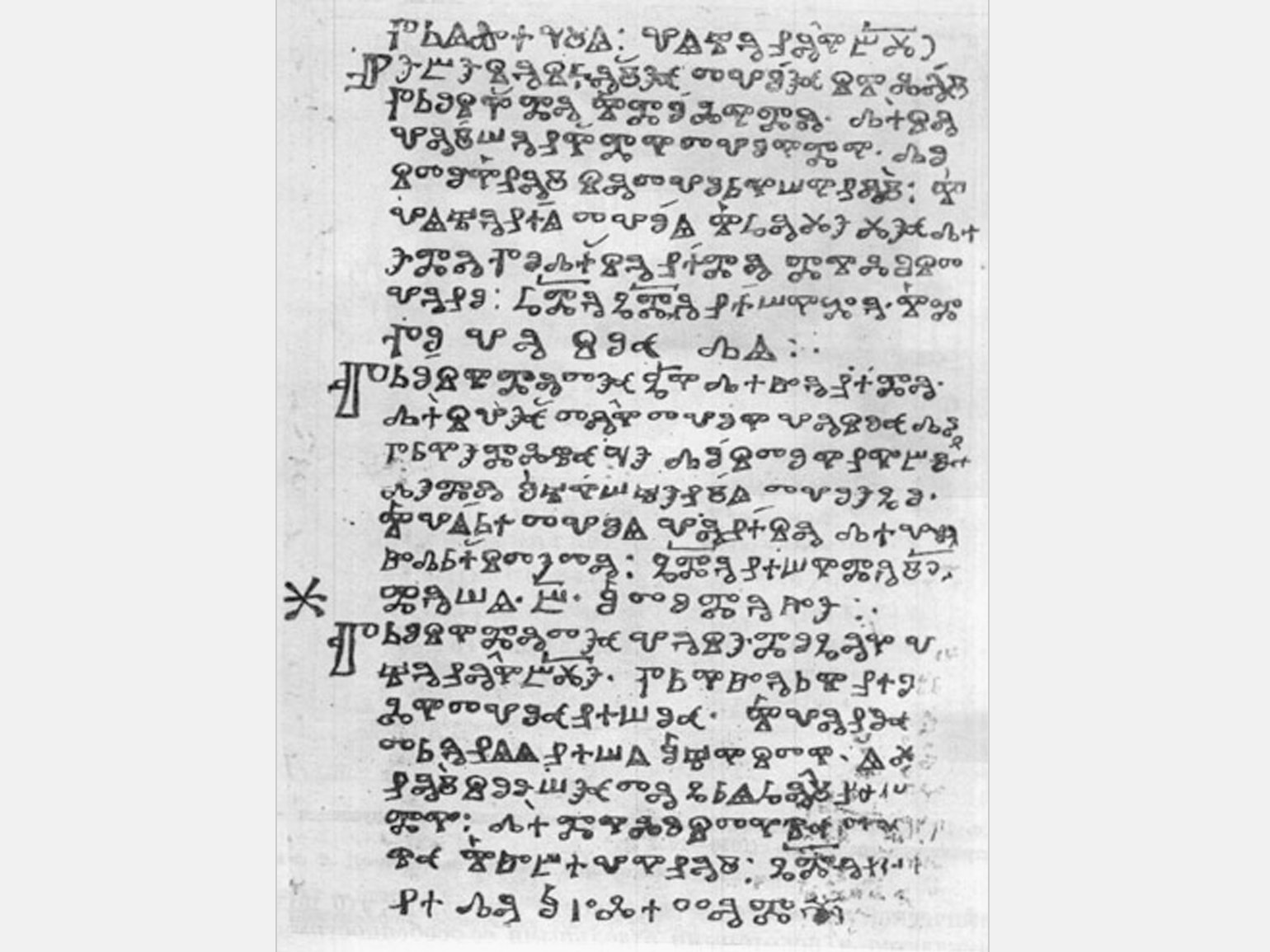
Юрий Остроменцкий
Графический и шрифтовой дизайнер, выпускник кафедры «Художественно-техническое оформление печатной продукции» МГУП, сооснователь магазина type.today и студии CSTM Fonts. Проекты CSTM Fonts получали награды в конкурсах European Design Awards, Granshan и «Современная кириллица».
Славянские шрифты нельзя назвать универсальными, потому что в зависимости от контраста, рисунка знаков и других деталей шрифт стилистически будет соответствовать определённой географии, веку или даже конкретной книге. Шрифты Times New Roman или Helvetica по рисунку никогда не были нейтральными или универсальными, но стали таковыми в силу частоты использования. Они так примелькались, что отчасти утратили выразительность.
Например, шрифт Izhitsa так часто используют в старославянском контексте, что его уже можно назвать универсальным, хотя у него есть конкретный исторический прототип.
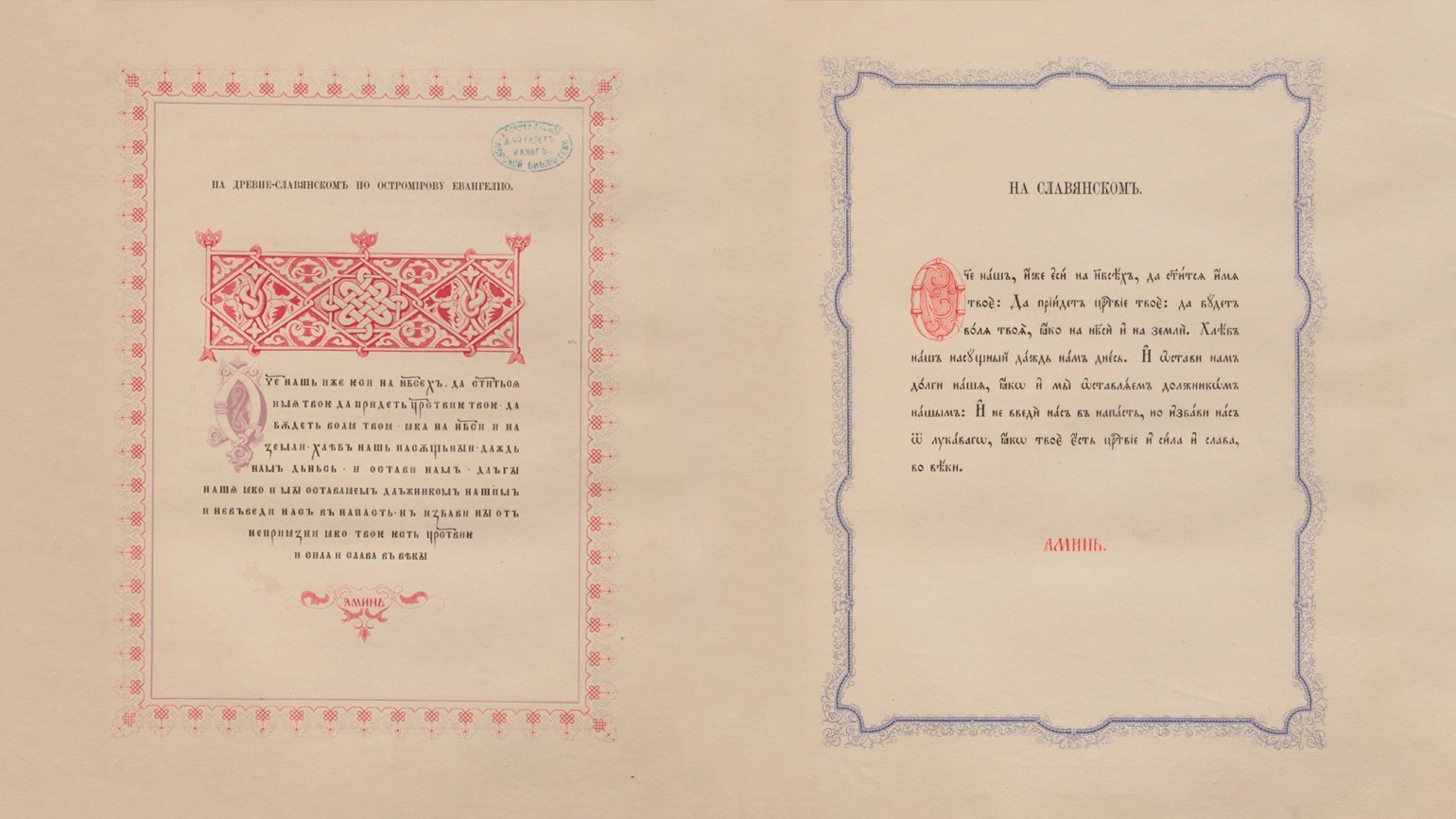
Дефицит качественных славянских шрифтов в науке и дизайне действительно существенный. Мне довелось общаться на эту тему с Виктором Марковичем Живовым, а сейчас я принимаю участие в переиздании работ Зализняка. Шрифтов, которые учёные могли бы использовать одновременно и в книге про Остромирово Евангелие, и про берестяные грамоты, — и вовсе не существует. Существующие шрифты чаще всего стилистически обращены к определённому времени и месту, что для учёных неприемлемо.
Сейчас я работаю над допетровским шрифтом с минимальными отсылками к веку или работе конкретного автора. Избавляюсь от контраста и ярко выраженных деталей, оставляя скелет знака. В этом суть моего эксперимента — что-то упростить, а что-то сохранить, чтобы шрифт стал современным, достаточно нейтральным, но при этом безусловно допетровским.
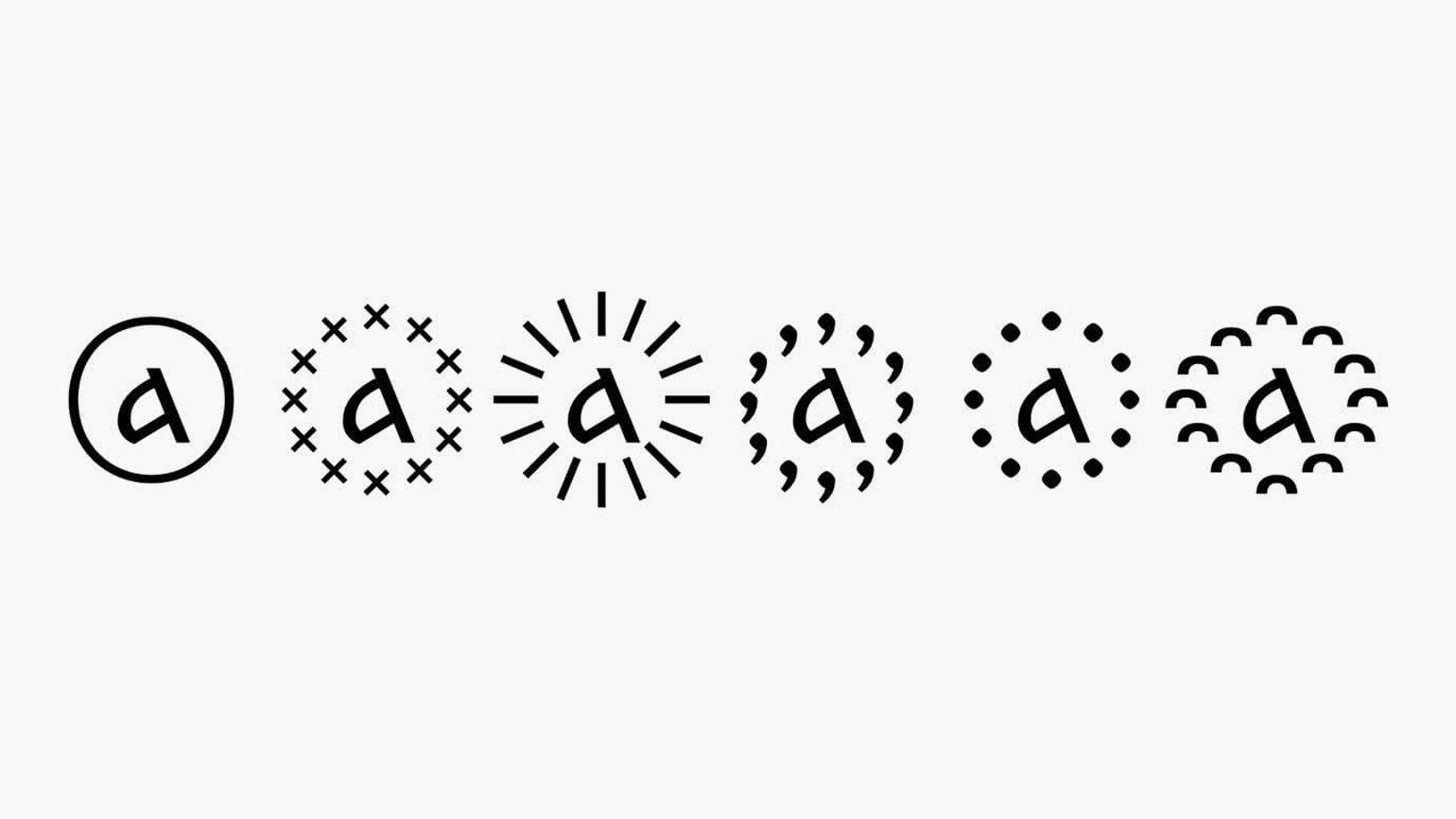
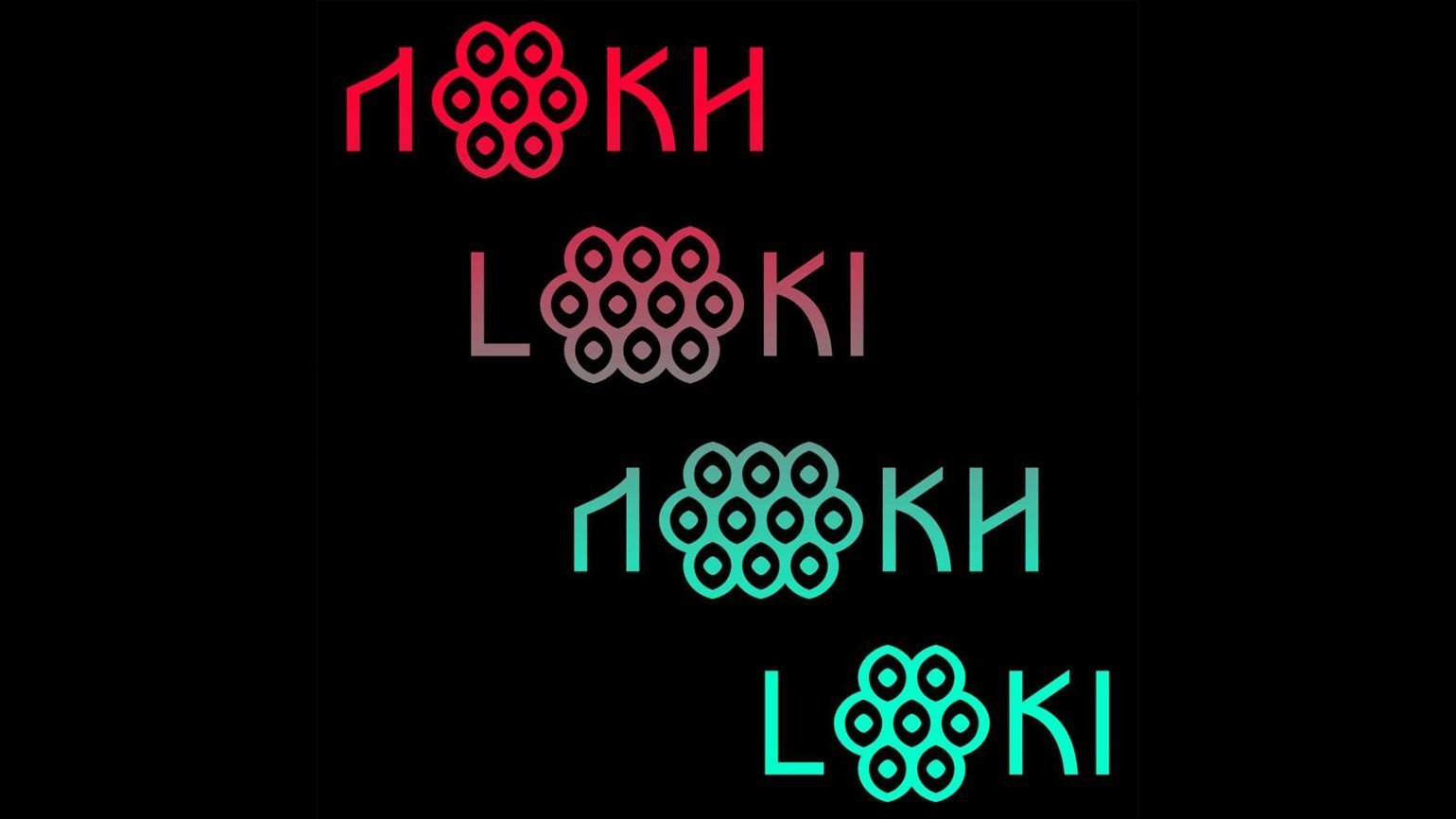
Мне кажется, что сейчас допетровский шрифт может выглядеть очень актуально. Например, мне нравится, как остромодно выглядит старославянская графика в коллекции Гоши Рубчинского.
Допетровская эстетика захвачена религиозно-национальной тематикой. Хочется, чтобы мы могли оценить красоту и выразительность этих букв вне идеологий и коннотаций. Мы могли бы относиться к допетровскому шрифту так же, как европейская культура относится к готическому, и использовать его вне идеологий. Я считаю, что у любого из нас ровно столько же прав на старославянский шрифт, сколько и у институций, связанных с религией и историей.
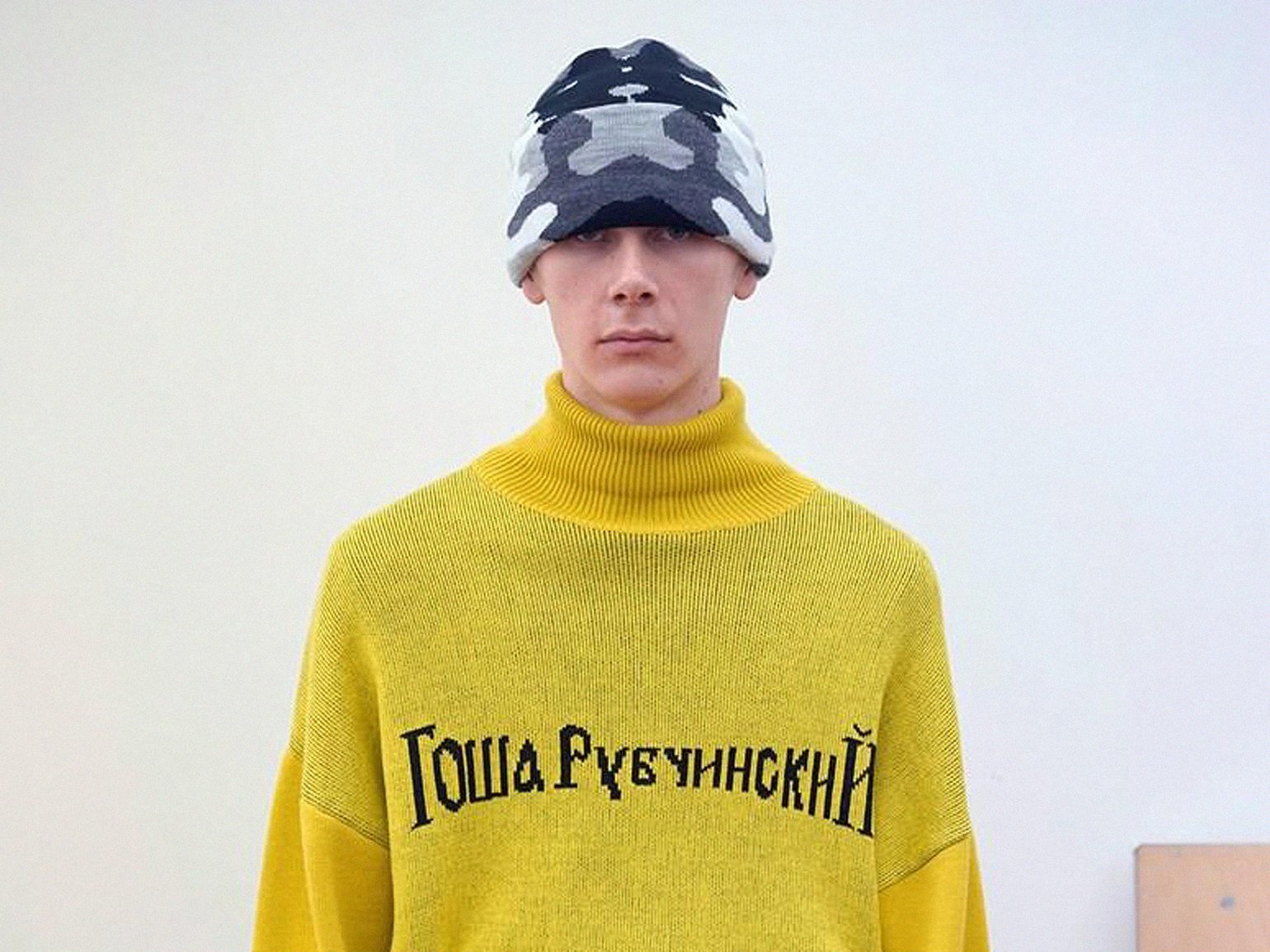
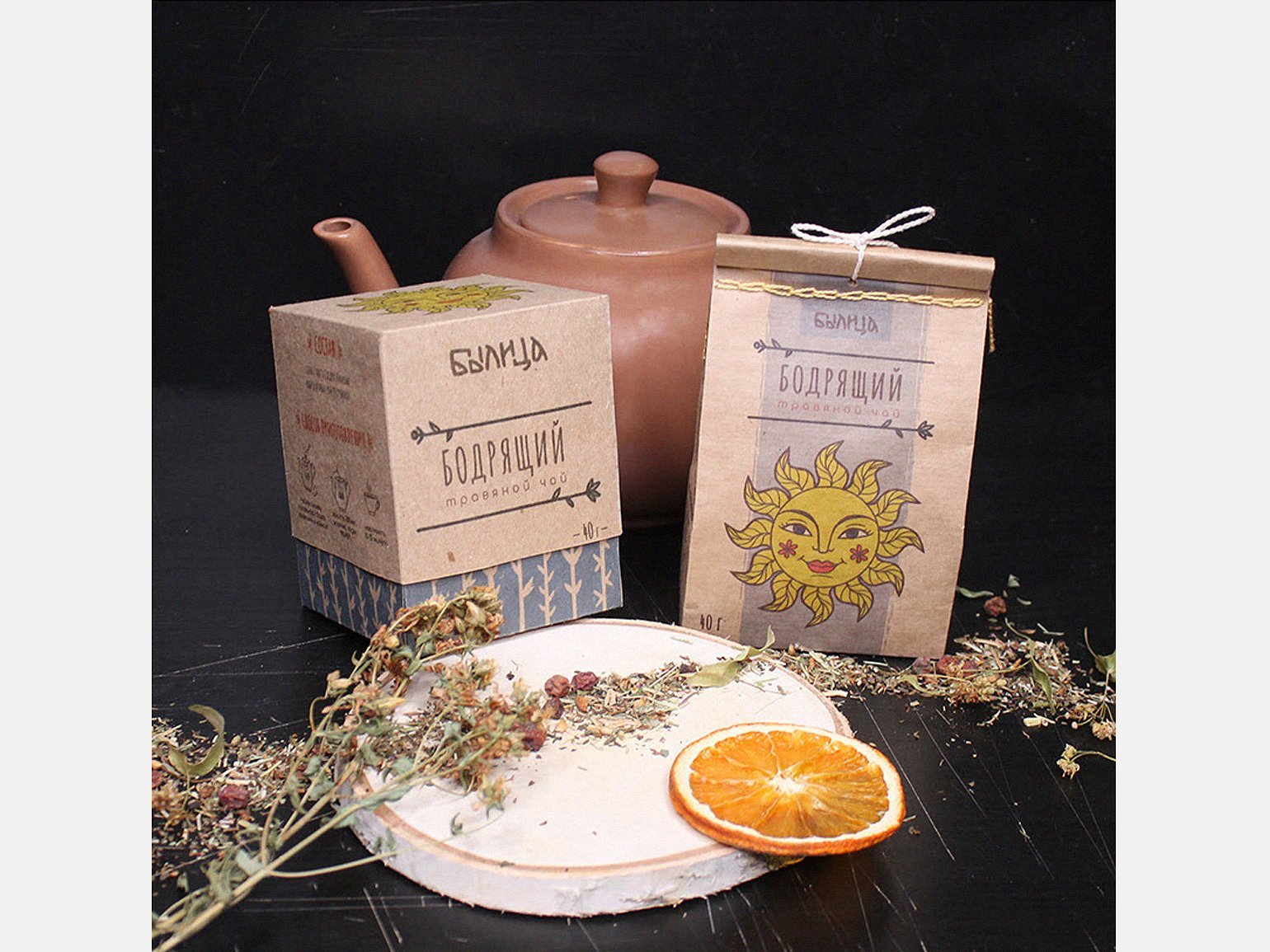
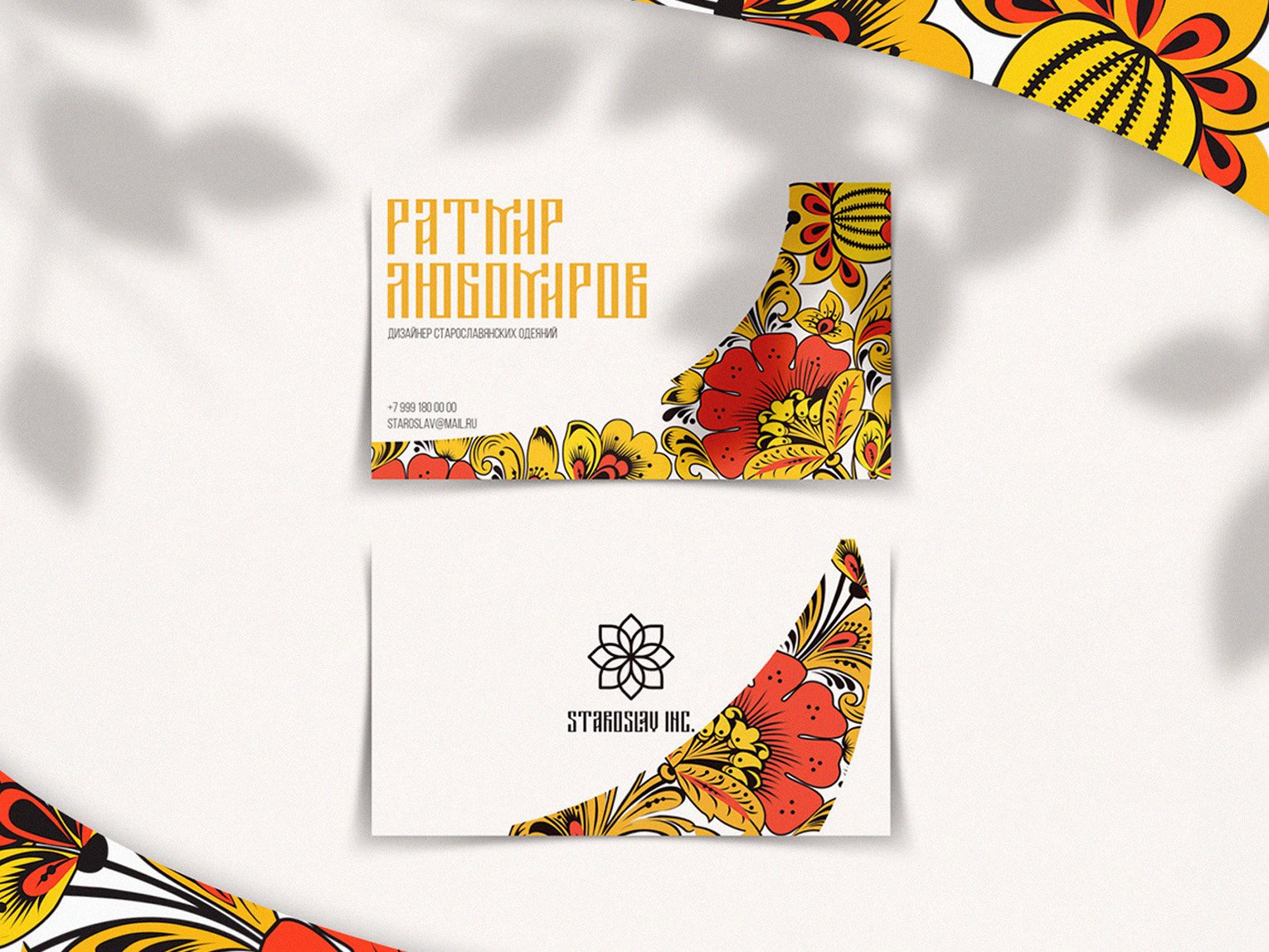
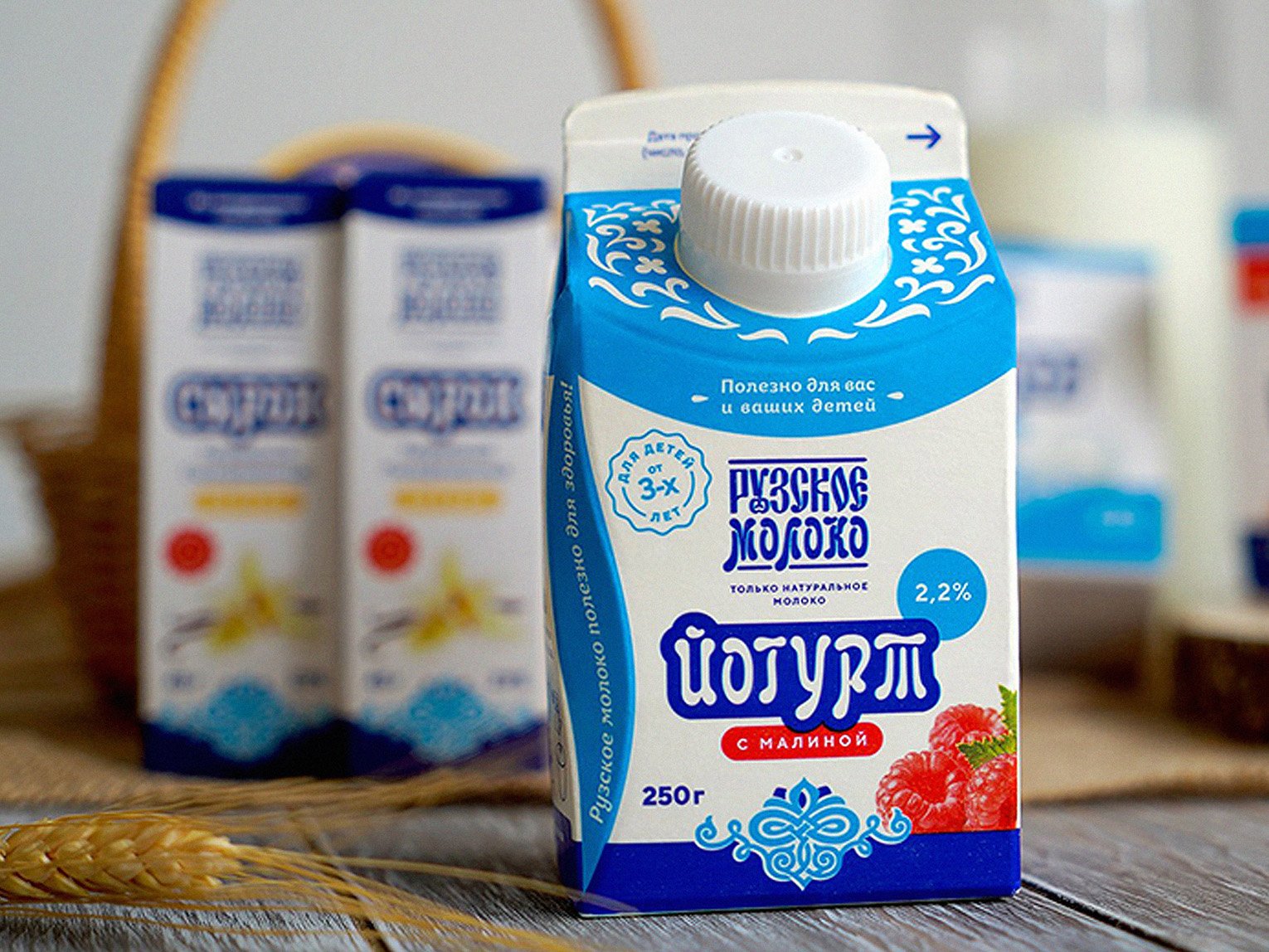
Африканские
Дизайнер Дуа Франсис хорошо знаком с африканской культурой, так как родился и вырос в Гане. Идея шрифта AYOR пришла к нему, когда он уже жил в Стамбуле и занимался ребрендигом для африканского ТВ-проекта.
Дуа Франсис
Дизайнер и арт-директор, увлекается искусством и технологиями, работает с 3D, выполнил десятки проектов для медиаиндустрии. Живёт в Стамбуле.
Работая над ребрендингом ТВ-компании Africa Magic, я погрузился в изучение культуры Нигерии, Конго и других стран Центральной и южной части Африки. Хотя сам родом из Ганы, я открыл для себя столько нового, что после окончания проекта для телевидения мне захотелось сделать что-то ещё. Так я решил создать шрифт с элементами нсибиди — древней символики Нигерии.
В интернете можно найти много этнических шрифтов, но не все они выполнены аккуратно. Мне нравится универсальность шрифта Helvetica, поэтому я старался сделать свой этнический шрифт лёгким и максимально универсальным.